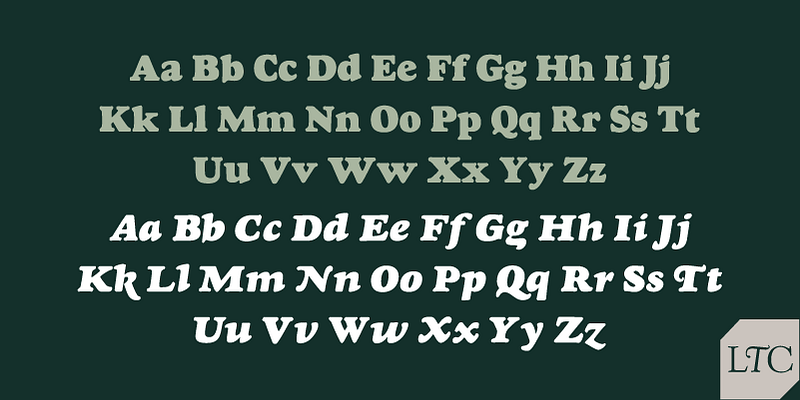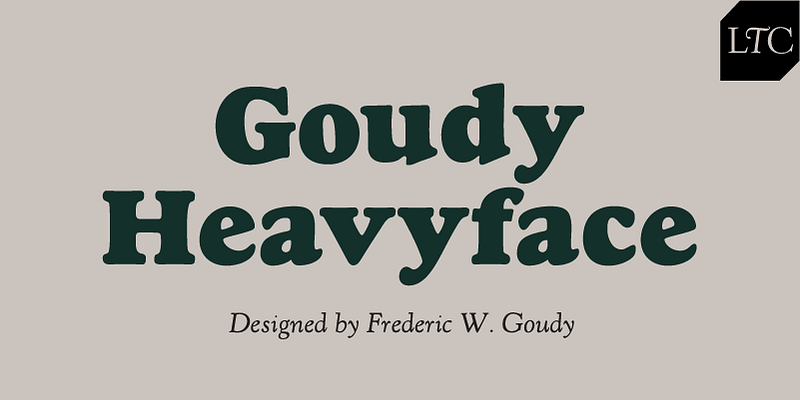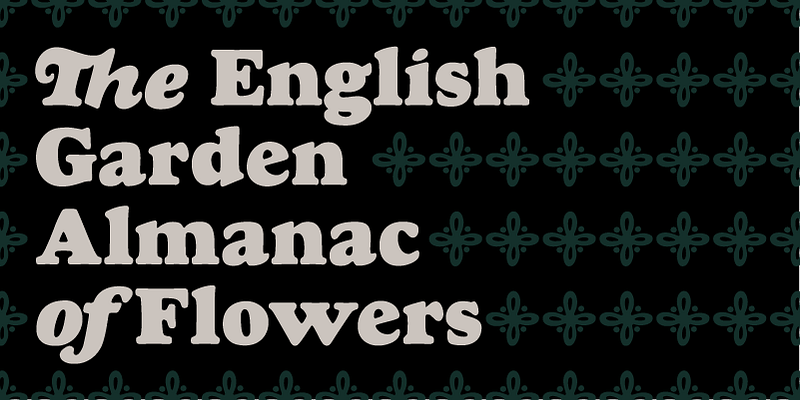
LTC Goudy Heavyface tiene el estilo de las letras llamativas para carteles de gran formato diseñadas por Frederic Goudy en 1925. Se creó para ser la respuesta de Lanston Monotype al entonces relativamente nuevo Cooper Black. La similitud es obvia, pero Goudy Heavyface tiene un toque distintivo de Goudy y un tono informal, lo que la hace única y una alternativa agradable al ahora omnipresente Cooper Black. Su diseño generoso permite su uso en un carteles de eventos, folleto o incluso en tarjetas de visita.